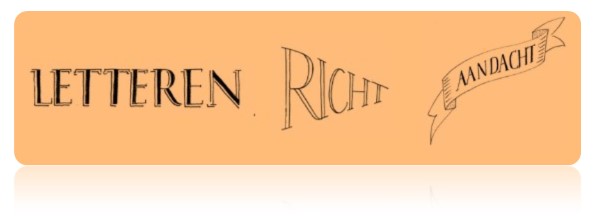
3. Leren schrijven – Voorproefje
Wat komt in dit hoofdstuk aan bod?
In dit hoofdstuk staan de beschrijving, de achtergrondinformatie en de theorie bij hoofdstuk 2: ‘Leren schrijven’ centraal. De student heeft deze informatie nodig om de opdrachten uit het werkschrift te kunnen maken. Naast de beschrijving ‘Leren schrijven?’ komen aan de orde:
• De schrifthandeling: de drie aspecten in samenhang.
• Schrijven: de drie domeinen.
• Les: relatie aspect en domein.
• Goed voorbeeld doet goed volgen.
· Domein 1: handschrift.
· Domein 2: typschrift.
· Domein 3: letteren.
De schrifthandeling: de drie aspecten in samenhang
Om een tekst (het aspect vorm) op papier, tablet of bord te schrijven of te typen, voer je handelingen uit (het aspect proces) met behulp van een pen, stylus, pencil, toetsenbord of krijtje (het aspect materiaal). Dat materiaal bevindt zich letterlijk tussen het proces en de vorm. Het model van de schrifthandeling beschrijft de drie aspecten proces, materiaal en vorm en hun samenhang. Je ziet dat ook terug in de overlap tussen de cirkels. Elk aspect beïnvloedt beide andere aspecten in een een-op-een relatie.
Proces en vorm
Het proces beïnvloedt de vorm. Een te lage pengreep (proces) vermindert bijvoorbeeld het zicht op je werk. Daardoor kun je de letters niet op elkaar afstemmen en heb je grote kans dat je slordig schrijft (vorm). Daarom is het aanleren van een goede pengreep zo belangrijk. Je oefent de pengreep door je leerlingen onder andere te laten kleuren en arceren. Pas als ze een goede pengreep hebben ontwikkeld, start je met het leren van cijfers en letters.
Omgekeerd beïnvloedt vorm ook het proces. Bijvoorbeeld: als je een modelvoorbeeld schrijft (vorm), dan doe je dat waarschijnlijk langzamer (proces) dan als je vlot aantekeningen maakt bij een college. In groep 3 schrijven je leerlingen langzaam omdat ze de lettervormen nog niet kennen. Ze kopiëren een voorbeeld zo precies mogelijk en dat kost tijd.
Materiaal en vorm
Materiaal faciliteert de vorm als je kiest voor taakspecifiek materiaal, dus: voor klein schrift een pen met dunne punt, voor groot schrift een dikke stift, plat krijtje of breed penseel.
Omgekeerd werkt je materiaal soms tegen, bijvoorbeeld als je schrift vlekt omdat je pen lekt.
Omdat de letters in groep 3 en 4 groter zijn, gebruik je in die groepen een pen met een dikkere penpunt dan in de bovenbouw.
Materiaal en proces
Materiaal beïnvloedt het proces: een prettige pen biedt bijvoorbeeld voldoende weerstand zodat je voelt wat je doet. Maar een slecht gekalibreerde digipen maakt je onzeker. Gevolg: je hapert en krijgt ‘stotend’ schrift. Een stotterende balpen geeft geen constante lijn en dwingt je om letterdelen opnieuw te maken. Dat is behoorlijk irritant en vergroot de spanning in je hand (materiaalhantering). Omgekeerd beïnvloedt het proces het materiaal: wie te hard op een fineliner of vulpen drukt, ruïneert de penpunt.
Proces, materiaal en vorm beïnvloeden elkaar dus. Je voert ze altijd in samenhang uit. Waar ze samenkomen ontstaat jouw eigen vaardigheid: de ‘Kennis en Kunde’ die daarom centraal in het model is opgenomen.
Omschrijf je de drie aspecten zo exact mogelijk, dan kom je heel dicht in de buurt van een definitie van schrift en dus ook bij een antwoord op de vragen: ‘Aan welke inhoud hebben mijn leerlingen behoefte?’ en ‘Wat bied ik hen dus in de les aan?’.
Schrijven: de drie domeinen
Als je aantekeningen maakt bij een telefoongesprek of college, als je een lijstje schrijft met boodschappen of things to do, als je een krabbeltje neerlegt voor je lief of als je mededelingen noteert op het bord gebruik je schrift.
Hoe kun je dat schrift het beste produceren? In zijn algemeenheid kun je handschrift gebruiken, typen of letteren: drie vormen van gedrag oftewel ‘domeinen’.
Die domeinen geven dus een antwoord op de ‘hoe-vraag’: ‘Op welke manier bied ik schrijven in de les aan?’
Net als de vraag naar de inhoud van schrift (de ‘wat-vraag’), is de hoe-vraag een relevante vraag voor Handschriftonderwijs en schrifteducatie. De manier waarop mensen – zeker ook jonge kinderen – reageren op letters en schrift heeft betekenis voor onderwijs, want op welke manier leren wij dat schriftgedrag zo goed mogelijk aan jonge kinderen aan en voor welke toepassingen? Waar zit schrift in ons eigen gedrag? Hoe kunnen we onze leerlingen stimuleren de mogelijkheden van schrift te gebruiken en bewust te kiezen?
Les: relatie aspect en domein
Dit schema verbeeldt de relatie tussen de aspecten en domeinen. Het omschrijft de samenhang tussen het ‘wat’ (de aspecten van schrift zoals weergegeven in het model van de schrifthandeling) en het ‘hoe’ (het schriftgedrag; de drie domeinen van schrijven).
In dit schema zie je dat je ieder aspect (proces, vorm en materiaal) met elk domein (handschrift, typschrift en letteren) kunt combineren tot een les of lessencyclus, bijvoorbeeld: